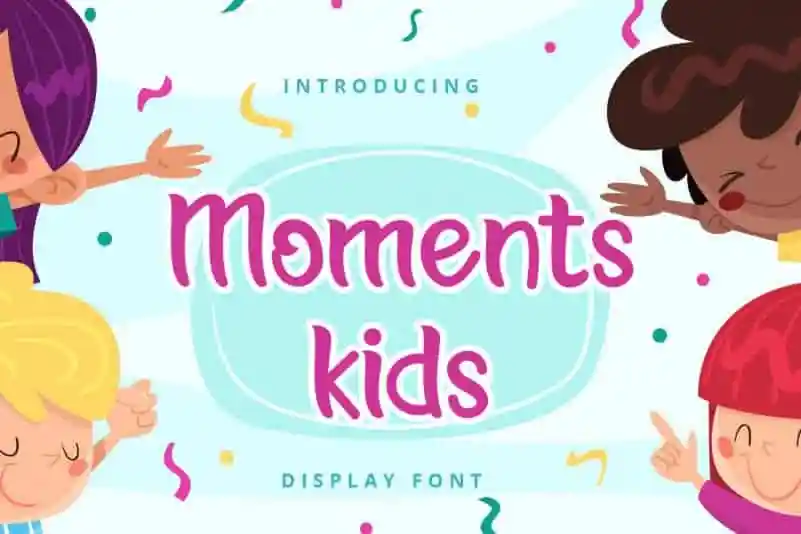
Moments kids Display Font – Download Grátis
Afont ‘Moments Kids Display Font’ é uma linda escolha para quem busca personalidade sem perder a simplicidade e elegância no design dos textos. Essa tipografia simples, mas de acabamento cuidadoso, irá dar um toque único aos seus projetos criativos, destacando-os em um mundo repleto de ideias inovadoras. Perfeita para aplicações como a criação de materiais educacionais para crianças, infográficos ou até mesmo para gráficas infantis, ela oferece uma maneira única e divertida de comunicar sua mensagem. Com ‘Moments Kids Display Font’, as suas ideias são certamente a primeira na fila!
Designer: planetz studio